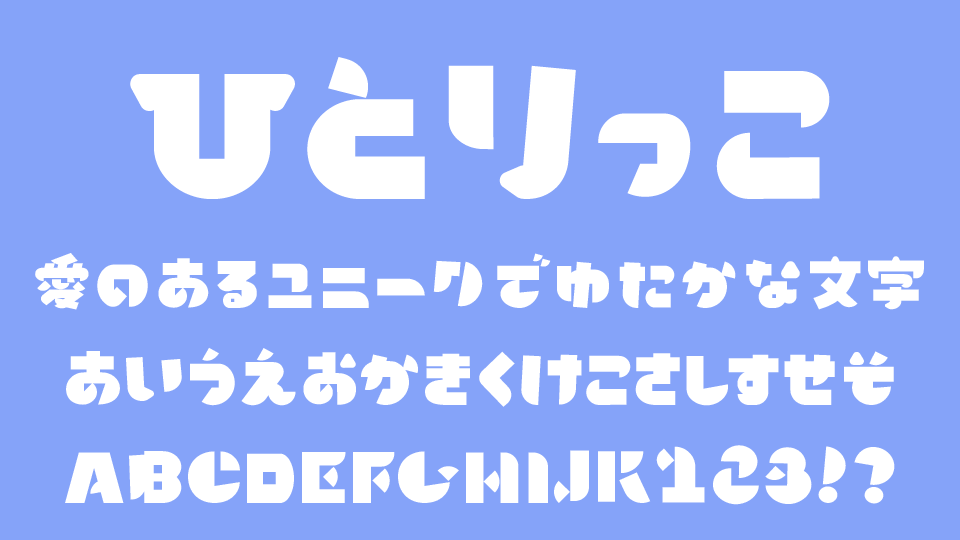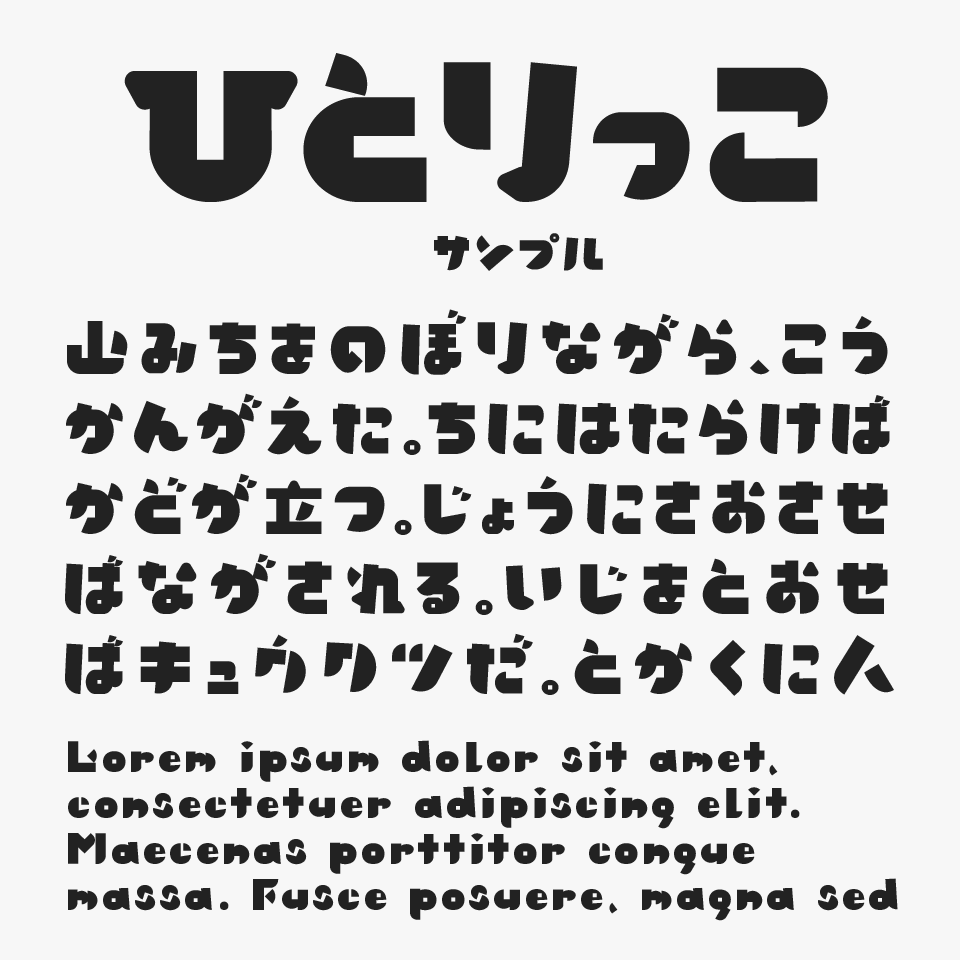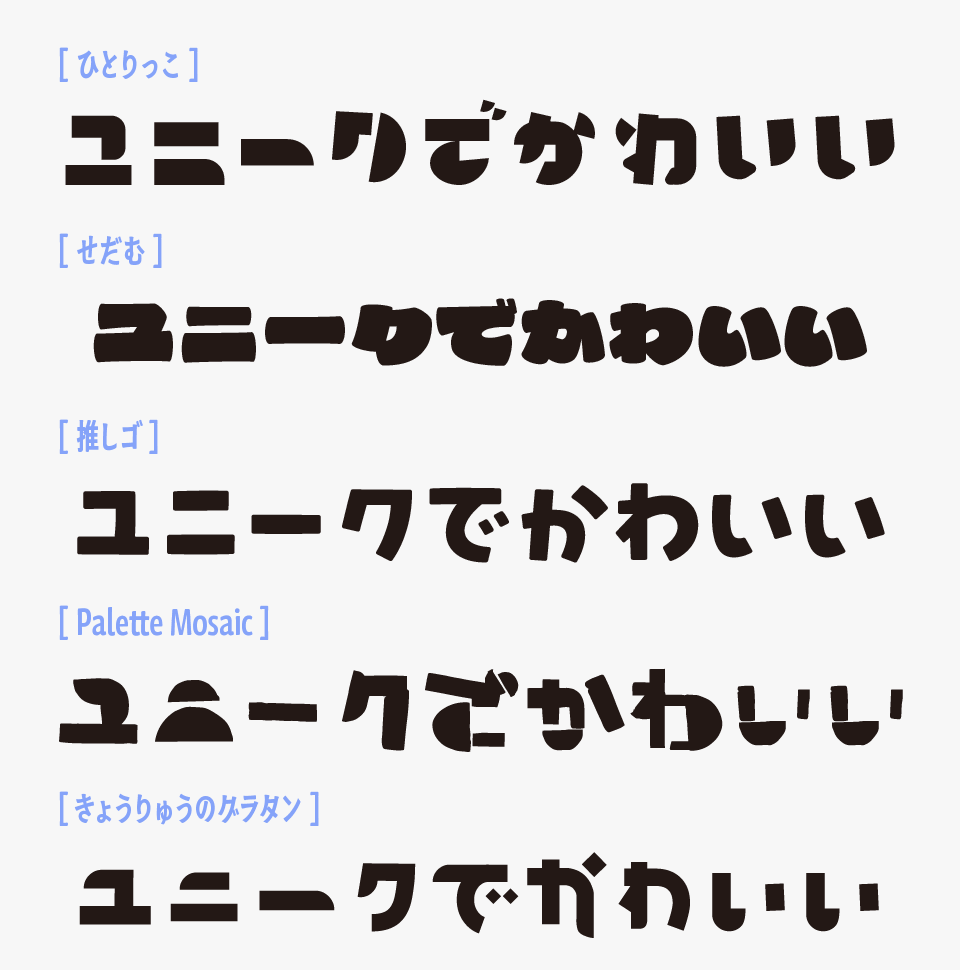
hitoricco(ひとりっこ)
ひとりっこフォントは、ポコっとして、どっしりとした太さと丸みをあわせ持つ、インパクト抜群のポップなデザインフォントです。
文字ごとに少しずつ形や傾きが異なり、手作業で切り貼りしたような味わいがあります。可愛らしさの中にも力強さがあり、タイトルや見出しでしっかりと視線を集められるフォントです。
YouTubeサムネイルやSNS画像、バナー、イベント告知、子ども向けコンテンツなど、元気で楽しい印象を伝えたいデザインにぴったりなフォントです。
ひとりっこフォントを、ほかの太くてポップなデザインフォントと比較してみると、丸みのある力強いシルエットと、手作りのようなラフな表情が特徴のフォントとなっています。